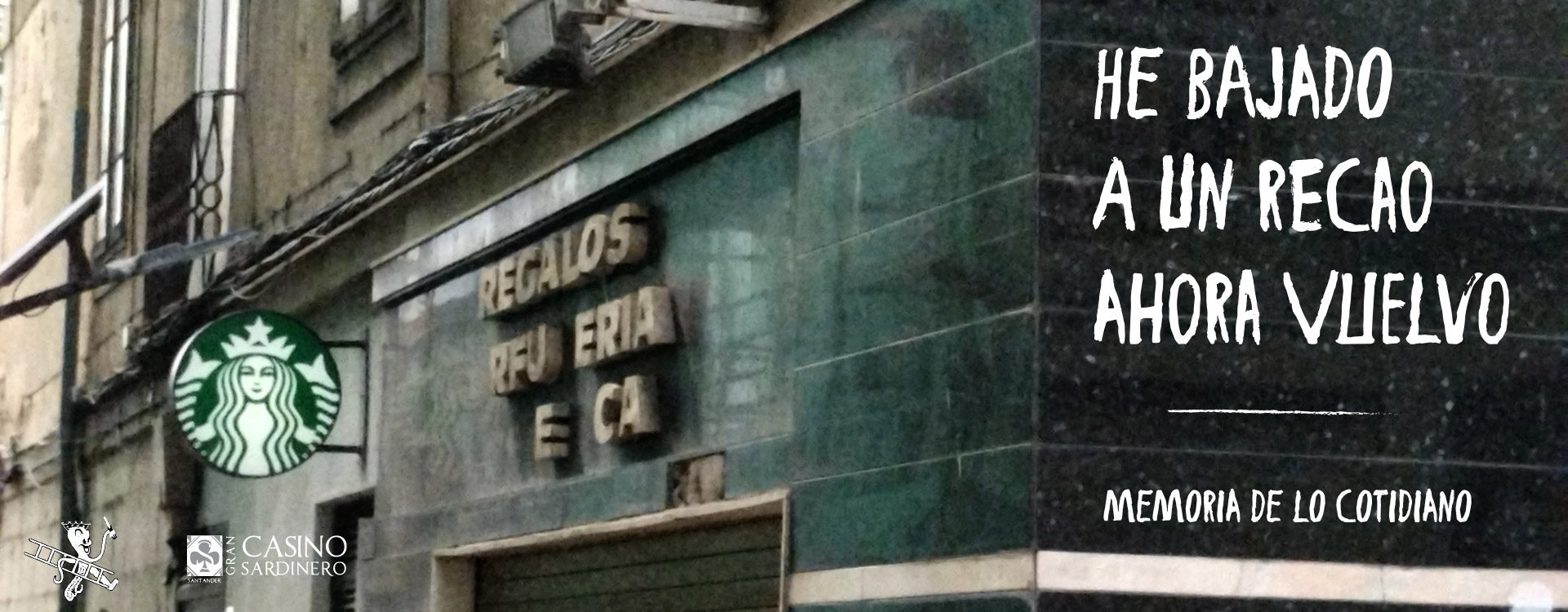
¿Qué es el
Patrimonio gráfico?
Los rótulos son un Patrimonio Gráfico concreto, cuando hablamos a las inscripciones o señales escritas o impresas que se utilizan para identificar o anunciar algo a nivel comercial o institucional.
Los rótulos pueden ser muy diversos y se encuentran en todas partes, desde los letreros de neón de los negocios hasta la cartelería y los podemos ver reproducidos en las etiquetas de los productos en las tiendas.
Estos elementos a menudo reflejan la historia, la cultura y el estilo de una época o lugar determinado. También tiene un alto valor social, por el comercio local de calles y barrios de nuestras ciudades, ya que esos rótulos y carteles forman parte de la identidad y memoria colectiva.
Además, muchos rótulos son considerados obras de arte por su diseño y estilo, ya que se ha realizado de manera artesanal (Rotulación en vidrio, Cerámica o forja de tipos) lo que les hace únicos y tienen valor histórico y cultural.
Por lo tanto, es importante proteger y preservar los rótulos para las generaciones futuras dado que forma parte de nuestra historia local y es una fuente creativa y cultural única.
patrimonio gráfico
de CantabriaSomos una Asociación cultural que tiene como objetivo principal, preservar el Patrimonio gráfico y visual de Cantabria. Para ello tratamos de poner en valor las muestras que se encuentran a día de hoy en las calles, concienciando a comercios, ciudadanos e instituciones que debemos conservar estos objetos, que generan memoria colectiva que trasciende de Patrimonio Visual y Gráfico de nuestras ciudades y que ayuda a conocer la historia de la ciudad desde otro punto de vista: el de sus calles y comercios. Dentro la preservación, con nuestro pocos medios y gracias a ciudadanos, comerciantes y seguidores de la Asociación, hemos rescatado y guardado más de 70 Carteles y material gráfico de Negocios abandonados o negocios cerrados.